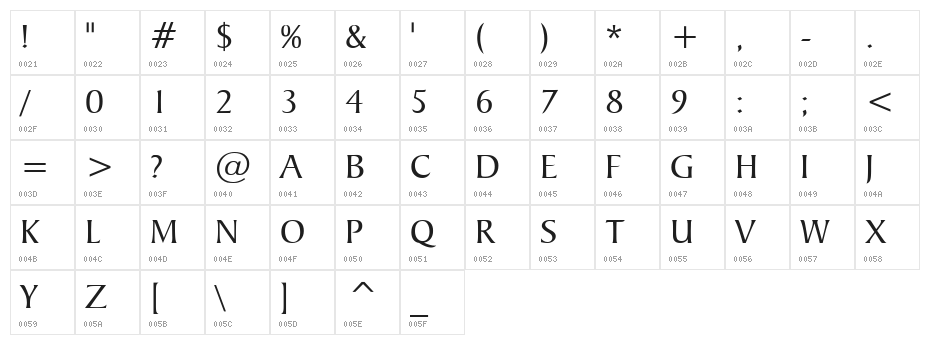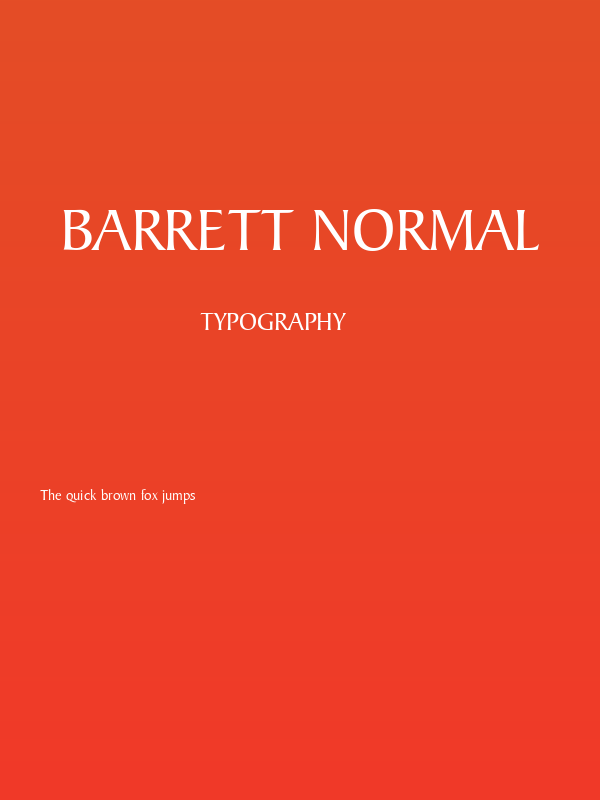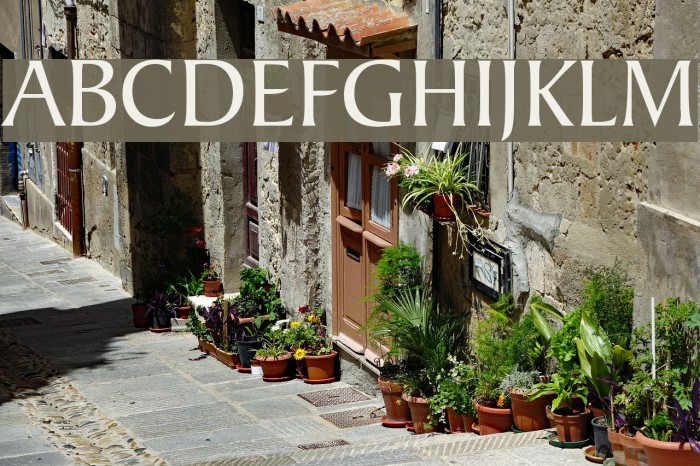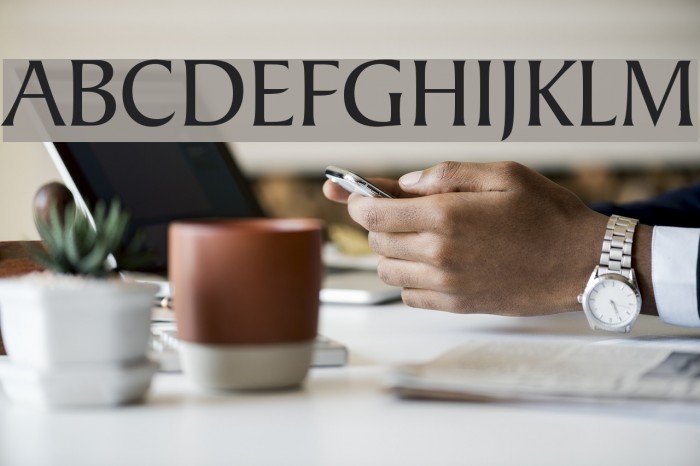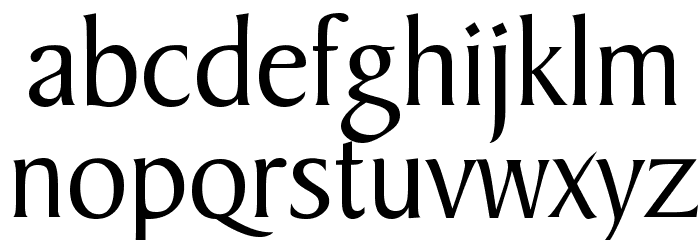
Barrett Normal Font
✎ Formal
| Categorías | Formal |
| Estilo general | Classic |
| Caso de uso | Headlines, Body text, Logos |
| Proyectos propuestos | Ideal for editorial design, book covers, formal invitations, and branding projects that require a touch of elegance. |